第二部分:从 TrueType GX 到可变字体
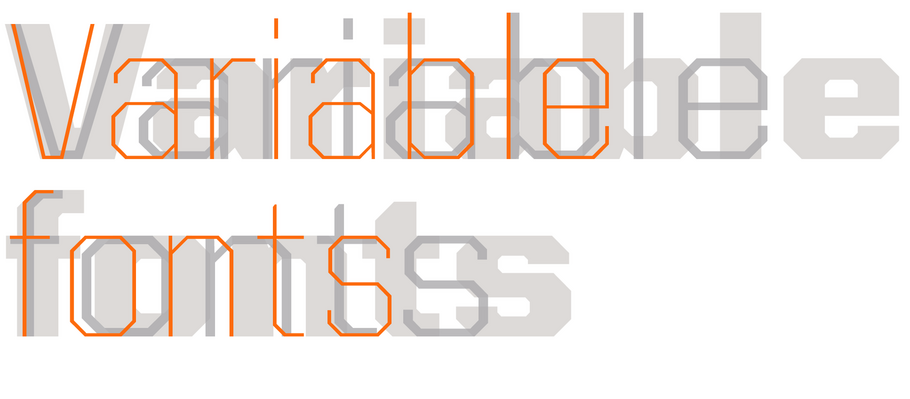
在第一部分中,资深字体设计师 Tom Rickner 讨论了促成 OpenType 1.8 版本发布这一事件背后 25 年的历史。在本文中,Tom 展望未来,为设计师和开发人员分享了他关于潜在用例的研究,并介绍了Monotype 的可变字体原型。
目前,OpenType 1.8 只是说明了我们想要去哪里,而没有说我们今天所处的位置。要实现这一目标,需要大量人员和组织(如谷歌、Adobe、微软和苹果)的大量工作。
到底需要发生什么?
- 操作系统需要添加对许多新定义的数据结构的支持
- 应用程序开发人员需要支持选择可变字体样式
- CSS 标准需要扩展以允许指定可变的字体样式
- 字体工具开发者需要更新他们的工具以输出可变字体
- 字体设计师和字体开发商必须实际制作字体
- 字体市场需要提供多种多样的字体
因此,我们仍然有足够的时间为未来的工作流程变化做准备。
未来的可变字体
未来的可变字体为字体设计者和用户提供了强大的控制力。虽然我们还没有为可变字体定义所有不同的用例,但当我们和其他行业参与者定义这种格式扩展时,其中一些用例已经出现在我们的思想前沿。
大型字体家族更易分发
更少的文件可能意味着更少的麻烦,特别是如果您是一名 IT 系统管理员,负责在整个组织中推广字体。一个单一的可变字体可以替代任何东西,从只有两个字重的小家族,到拥有无数变化轴(如字重、字宽、视觉字号等)的大家族。无论是 5 个、10 个还是 50 个样式,如果不同的样式可以用相似的点结构来描述,它们就有可能被构建成可变字体,从而大大减少交付和安装所需的文件数量。
压缩
将多种样式打包在一个文件中也可以提供大量的字体家族压缩。我将在以后的文章中分享更多的细节,但这里的核心信息是,你给可变字体添加的样式越多,每个样式的大小就会变得越小。作为一个例子,下面的图表显示了我们创建的小型测试字体系列所需的字节大小,无论是作为单独的 TTF,还是作为从这些单独的 TTF 创建的可变 TTF。
我们添加的样式越多,节省的总静态字体大小的百分比就越大。然而,省出的体积实际上比图中所示的还要多,因为这些数字只表示存储的样式。在大多数情况下,大家庭有许多风格完全是由这些母版风格创建的。在这里的示例字体中,这 12 种输入字体用于生成 8 个字重,横跨 3 个字宽、2 种造型(罗马正体 vs 意大利斜体),这对应于存储在单个可变 TTF 中的 48 种独立字体样式。
存储这 48 个输入 TTF 约需 555k 空间,现在能以一个可变 TTF 提供和渲染,只需 66k。这节省了大约 88% 的文件大小。虽然节省的程度非常依赖字符集的大小、复杂性的程度或微妙的设计、轴的数量,以及子样的数量,但这个数字是将一个字体家族构建为可变字体所节省的空间的近似期望。
更微妙的样式控制
在早期的数字字体中,对于给定的字体,您可能有 4 种样式可供选择:常规、斜体、粗体和粗斜体。当字体设计师开始设计更大的字体家族时,用户可以获得其他字重,有时还可以获得其他字宽。随着字体设计师开始在他们的工具中使用插值功能,创建带有大量样式阵列的更大家族的能力比以往任何时候都更容易。但是,即使今天向用户提供了更多的字体选择,人们还是希望能够选择稍微粗一点点,或者稍微窄一点点的字体。
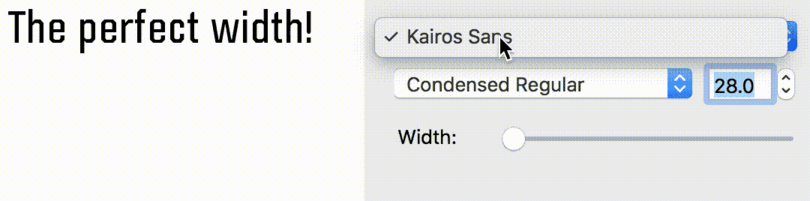
可变字体可以支持这种选择,只要应用程序为您提供一个用户界面,用于在设计空间中选择任意子样。到目前为止,我们看到的最常见的界面是 “滑块”,它类似于声音混合板上的渐变器。这允许用户拖动旋钮以沿设计轴选择坐标。通过这种机制,用户可以从选择一个预设子样(如 Condensed SemiBold)开始,然后他们可以根据需要微调滑块以获得稍微宽一点、稍微粗一点的内容。
响应式排版
五百多年来,我们在设计文件时都考虑到了印刷。随着桌面出版和可缩放的轮廓字体格式(如 TrueType、PostScript 和 OpenType)的出现,我们开始为屏幕和打印设计。但如今,我们对 “屏幕” 的定义因你碰巧正在观看的特定设备而发生巨大变化。为 72 或 96 dpi 设计的日子已经一去不复返了。常见的 640 × 480 或 800 × 600 的屏幕尺寸已经不见了。拥有不断扩展的属性和像素配置的过多设备意味着为 “屏幕” 设计需要一定程度的布局灵活性,而这在前五个世纪的排版设计中是没有考虑到的。
“响应式排版” 是我们用来描述文本、图形和其他媒体在当前设备物理限制下的动态和响应式排版的术语。属性,明显如字号、行距,或行长度可能会随着屏幕的不同而改变。要想获得最佳的阅读体验,需要以微妙而高效的方式调整各种属性。稍微压缩整体宽度可以减少别扭的连字断行和两端对齐。标题字的加宽可以让人在不增加整体字号的情况下保持完全两端对齐的一栏,同时不会占用太多的垂直屏幕空间。
具有可变字体的灵活性必不可少,但这还不足以实现响应式排版的梦想,这点必须指出。此外,还需要在创作和显示环境中提供额外的支持,以提供许多人希望的增强用户体验。
视觉字号调节
在照相排版出现之前,一个字体通常被设计成许多不同的主字号大小。某些基本特征,如间距、笔画对比度和细节程度,会随着字号大小的增加或减少而改变。例如,在较小的文本大小时,我们通常希望有更多的开放字怀和间距,或许还有更大的 x 高度。此外,像衬线这样的精细细节也可以在加粗并降低粗细对比后变得更好。随着字体大小的增加,我们可以允许更大的对比度、更精细的细节和更精细的间距。
当向照相排版的转变发生时,许多系统开始将一个单一的照排母版应用于每个字母,他们依赖使用镜头以线性方式缩放字体。当这些照相母版(或热金属字体的图稿)被数字化以创建第一个数字轮廓时,字体公司通常使用正文字号的母版,比如 12 点。这个数字轮廓然后被用来表示所有点的大小,除了可能提供一个字号变体,如 “display”。当这种情况发生时,我们失去了一些东西,即特定尺寸的字体,优化不同的设计特征,以提供最高质量的排版可能。
OpenType 1.8 中包括了视觉字号的 `opsz` 标签,作为可识别的预定义轴标签之一。然而,我应该指出,就像响应式排版一样,我们需要操作系统和应用程序的支持,才能自动无缝地执行这个特性。
介绍可变字体 Kairos Sans
我们的下一步将在很大程度上取决于我们的客户的需求,如开发人员、网页设计师和出版商。我们想制造能解决实际问题的产品。为了帮助进行评估,我们将发布样本字体供您使用和试验,以衡量兴趣和有用性。
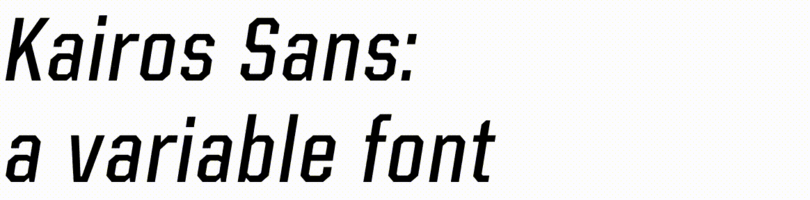
第一个字体是 Terrance Weinzierl 的 Kairos Sans 字体家族的原型。这种字体中有趣的特性是除了更常见的字重和字宽轴外,还有一个斜体轴。这种字体很适合同时存储直立和斜体样式,因为斜体大部分是倾斜的罗马体。用户是否能从选择不同坡度的能力中找到价值是我们好奇的事情。